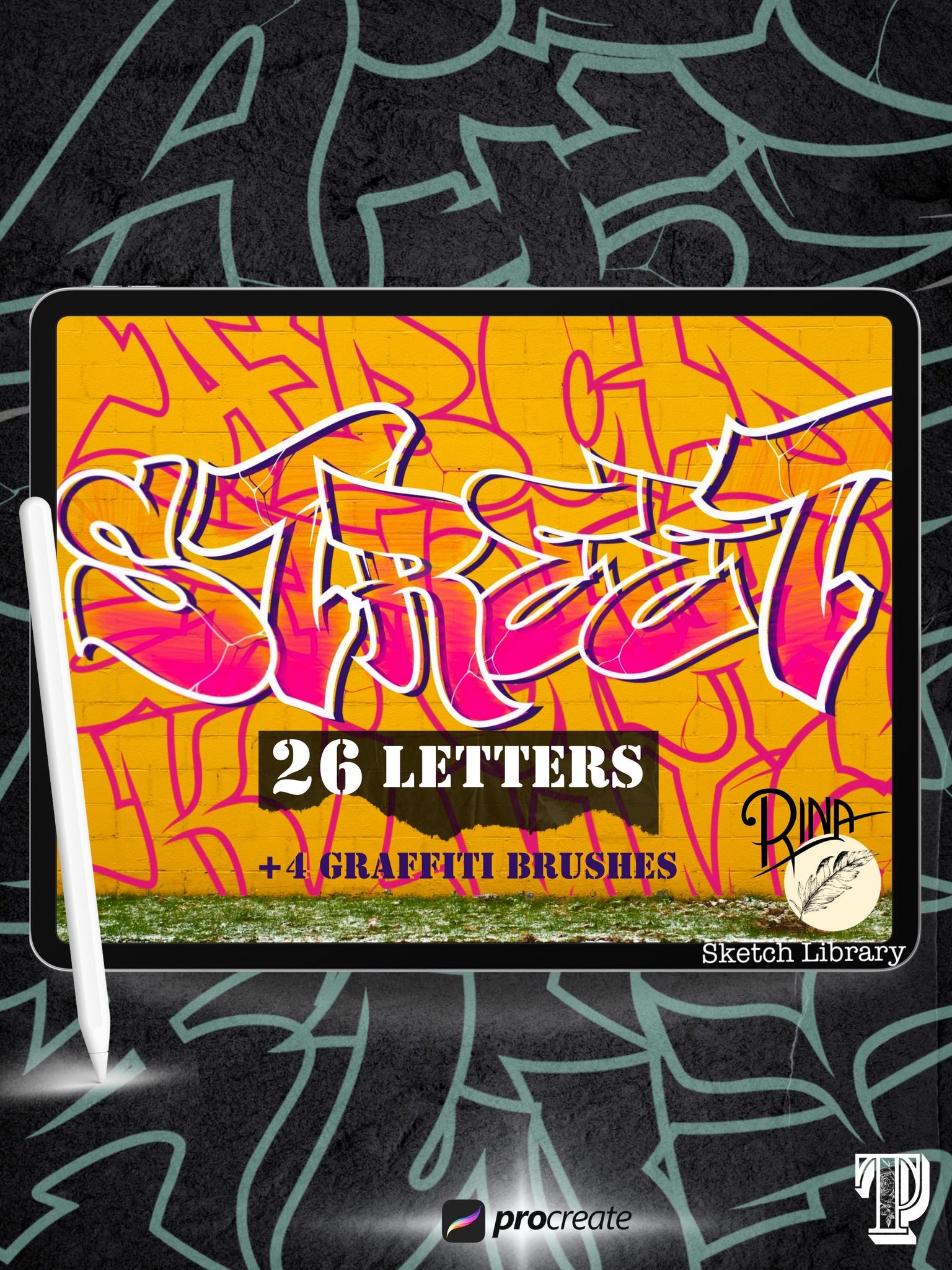
Dans ce set de pinceaux, il s'agit d'un alphabet Graffiti Bubble Style de la Street Artist : Rina Jonson, pour l'application PROCREATE.
En quelques secondes, vous pouvez créer un mot original sur n'importe quel fond.
Tous les pinceaux sont originaux et créés dans le style street art.
- 26 lettres - Alphabet